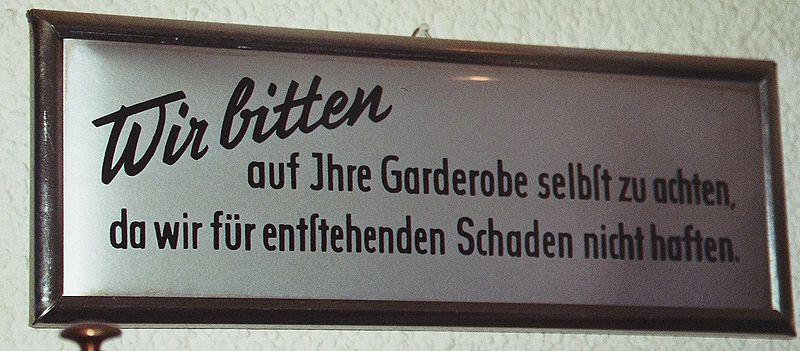
Du könntest ihm ein paar Beispiele zeigen, in denen eine Antiqua mit langem s verwendet wurde; damit er sieht, daß es sowas wirklich gibt.
Und dann ein paar bekannte Beispiele (da wird sich wohl nur Fraktur finden lassen), damit er sieht, daß das lange s weit verbreitet ist und viele es kennen.
Du könntest ihm ein paar Beispiele zeigen, in denen eine Antiqua mit langem s verwendet wurde; damit er sieht, daß es sowas wirklich gibt.
(Selbstcitat; hatte ich oben schon mal gepostet.)
Du könntest ihm ein paar Beispiele zeigen, in denen eine Antiqua mit langem s verwendet wurde; damit er sieht, daß es sowas wirklich gibt.
Dieses Bild ist doch eher ein schlechtes Beispiel, „selb?t“ und „Jhre“, aber wenigstens zeigt es, dass es das ? auch in der Antiqua gibt.
Du könntest ihm ein paar Beispiele zeigen, in denen eine Antiqua mit langem s verwendet wurde; damit er sieht, daß es sowas wirklich gibt.
Tatsächlich, das wäre wohl eine gute Idee.
Bis heute fortlebend:
Du könntest ihm ein paar Beispiele zeigen, in denen eine Antiqua mit langem s verwendet wurde; damit er sieht, daß es sowas wirklich gibt.
In jenem älteren thread sind noch weitere.
@Joshua und Frakturfreak: Ja, ich finde auch dass man ein J statt einem I wirklich niemanden sehen lassen sollte... :wink:
Dieses Bild ist doch eher ein schlechtes Beispiel, „selb?t“ und „Jhre“, aber wenigstens zeigt es, dass es das ? auch in der Antiqua gibt.
@Joshua und Frakturfreak: Ja, ich finde auch dass man ein J statt einem I wirklich niemanden sehen lassen sollte... :wink:
Das ist durchaus eine übliche Form für das I. Zur Unterscheidung hat das J eine Unterlänge und manchmal noch einen Querstrich. So ist es ja auch in der lateinischen Schreibschrift! Siehe beispielsweise FF Schulbuch Süd:
Das „selb?t“ betrachte ich natürlich auch als falsch. Ich habe jedoch den Eindruck, daß sich in der Antiqua in der Verbindung „?t“ das lange ? länger gehalten hat; mehrere Beispiele habe ich schon dafür gesehen. Bei mir um die Ecke gibt’s auch ein „Ga?thaus zum Eisernen Kreuz“ (das inzwischen anders heißt, die alte Beschriftung aber noch trägt).
… und was, nebenbeibemerkt, für eine schöne ch-Ligatur!
Dieses Bild ist doch eher ein schlechtes Beispiel, „selb?t“ und „Jhre“, aber wenigstens zeigt es, dass es das ? auch in der Antiqua gibt.
@Joshua und Frakturfreak: Ja, ich finde auch dass man ein J statt einem I wirklich niemanden sehen lassen sollte... :wink:
Das ist durchaus eine übliche Form für das I. Zur Unterscheidung hat das J eine Unterlänge und manchmal noch einen Querstrich.
Das es diese Buchstabenform gibt, weiß ich auch, aber es sieht etwas ungünstig aus. Ich finde es auch schade, dass in vielen gebrochenen Schriften großes I und J die gleiche Glyphe sind.
Das „selb?t“ betrachte ich natürlich auch als falsch. Ich habe jedoch den Eindruck, daß sich in der Antiqua in der Verbindung „?t“ das lange ? länger gehalten hat; mehrere Beispiele habe ich schon dafür gesehen. Bei mir um die Ecke gibt’s auch ein „Ga?thaus zum Eisernen Kreuz“ (das inzwischen anders heißt, die alte Beschriftung aber noch trägt).
Ich glaube, das trifft auch auf ?ch zu. Regelgerecht ist aber nicht, da sind wir uns ja einig.
Ich find es sieht furchtbar aus... Mit der Meinung befinde ich mich (nicht nur mit dem verehrten Kollegen Frakturfreak) auch in bester Gesellschaft. Tschichold schreibt dazu im Meisterbuch der Schrift: »Wenn dem I ein oder zwei l folgen, so entstehen in der Endstrichlosen drei nackte senkrechte Striche. In einer guten Schrift sind diese aber nicht von gleicher Größe und Stärke. Zumindest ist das I um eine Spur dicker. Das muß genügen.« :rockon:
alle haben recht - hier steht Gewohnheit gegen Amtsschimmel!
in der "Zeitung des Vereins Deutscher Eisenbahnverwaltungen, 1874" wird im Artikel: Das Schienenprofil der Ostbahn, das lange und das runde s (Schluss-s) in einer Antiqua verwendet.
im Duden von 1926, Abschnitt I. Zur Rechtschreibung, Untergruppe Über die S-Laute" steht zum Schluss: " Zusatz. Aus der Fassung der Regel geht deutlich hervor, daß die mehrfach versuchte Anwendung eines langen s in lateinischer Schrift für das s in der deutschen Schrift unzulässig ist." (ich bin zu dusselig, hier die echten Typen einzubinden).
Dafür ist der kleine Duden aus Leipzig von 1953 bis auf die Titelseite durchgängig mit langem ? gesetzt.